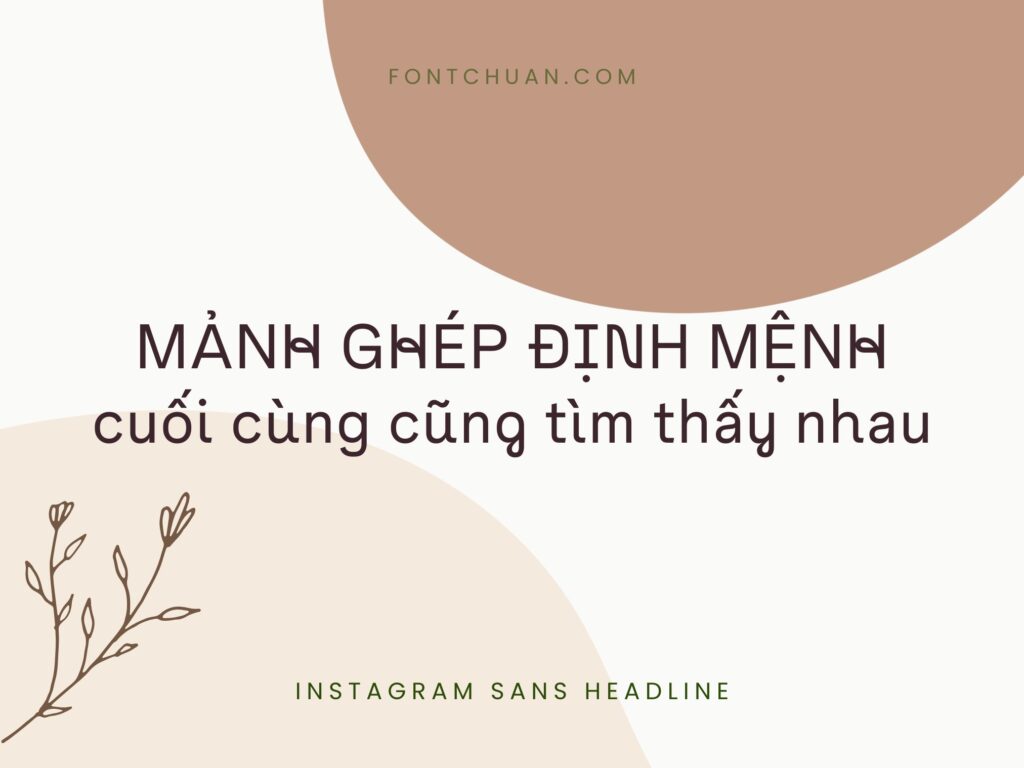
Font Instagram Sans Ui Trọn Bộ (Headline)
Instagram Sans là bộ font tùy chỉnh được thiết kế bởi Colophon Foundry, ra mắt vào năm 2022 như một phần của việc làm mới thương hiệu Instagram. Lấy cảm hứng từ sự kết hợp giữa các phong cách grotesque và hình học, font này phản ánh sự đơn giản và tinh tế mà nền tảng Instagram hướng tới. Với các phiên bản như Regular, Light, Medium, Bold, Condensed và Script, Instagram Sans mang đến sự linh hoạt cho các thiết kế. Font này được sưu tầm và đăng bởi thành viên của Font Chuẩn, hỗ trợ tiếng Việt và nhiều ngôn ngữ khác.
Instagram Sans có cấu trúc chữ rõ ràng, độ dày đồng đều và các đường nét mềm mại, tạo nên sự cân bằng giữa tính thẩm mỹ và khả năng đọc. Font này phù hợp cho các thiết kế liên quan đến thương hiệu, truyền thông xã hội, tiêu đề và nội dung số. Đồng thời, Instagram Sans cũng có thể được sử dụng như một Font chữ ẩm thực, giúp các nhà hàng, quán ăn và thương hiệu thực phẩm tạo nên sự hiện đại, tinh tế và thân thiện trên menu, bao bì hoặc các ấn phẩm quảng cáo. Ngoài ra, font vẫn được tận dụng hiệu quả trong các ngành quảng cáo, công nghệ, giáo dục, bất động sản, cũng như các sự kiện như lễ hội, sinh nhật, ngày Nhà giáo và Valentine.